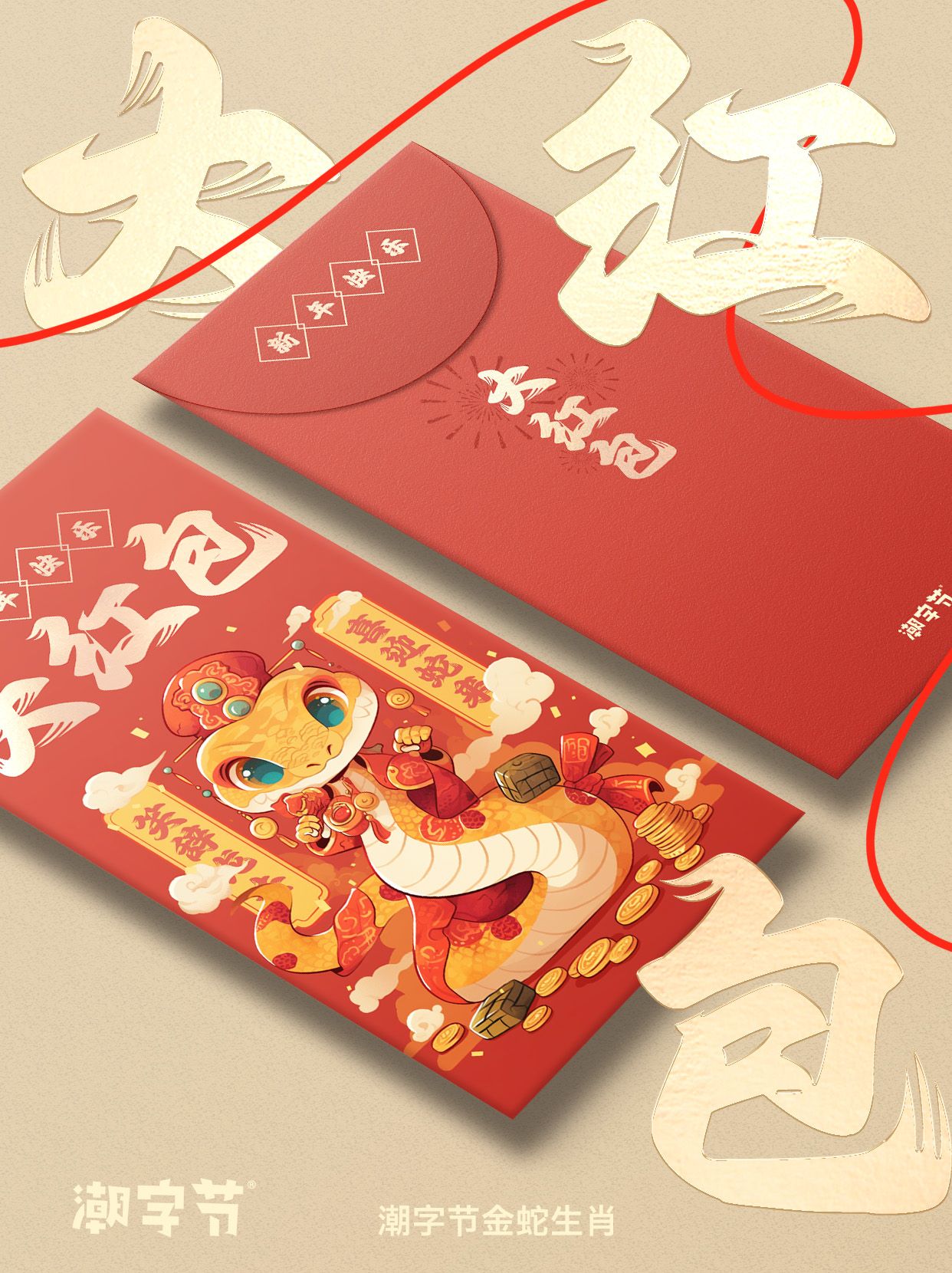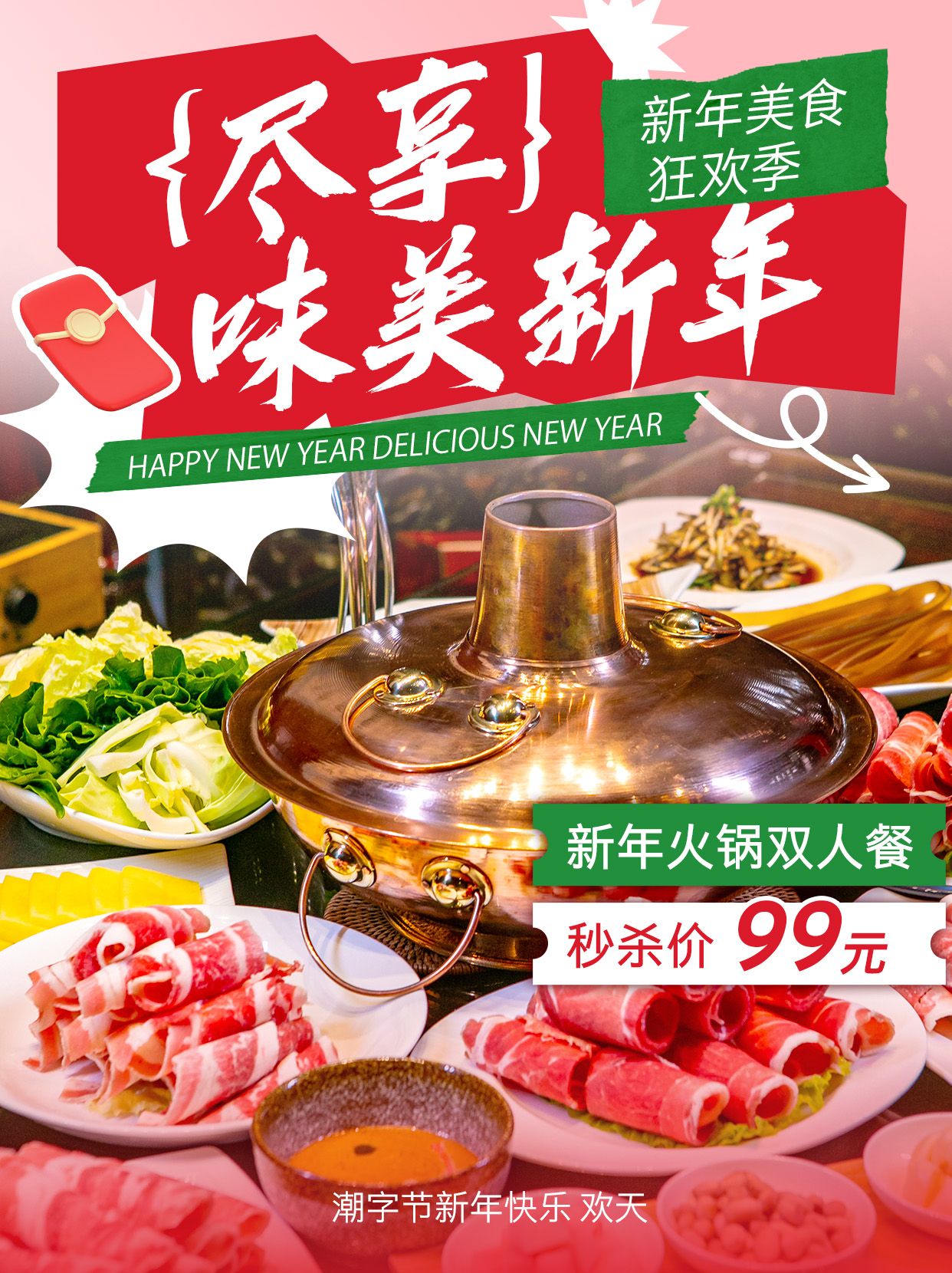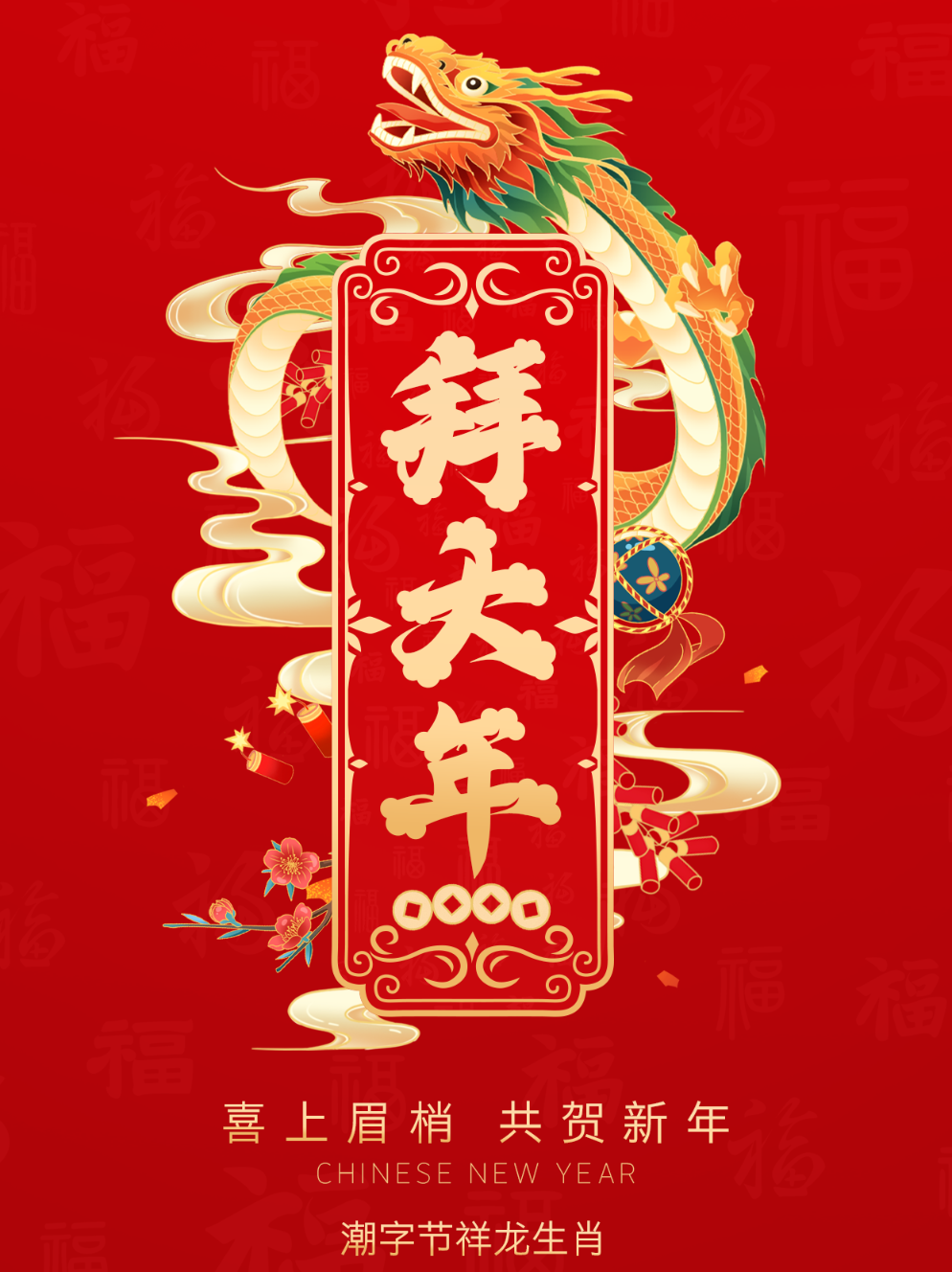
🎉揭秘三款国潮包装里常见的字体🎨潮字节字体大赏🐉
亲们,是不是每次看到那些充满国潮元素的包装设计,都忍不住想多看两眼?今天,就让我来揭秘三款让你包装瞬间提升格调的神级字体——“潮字节金蛇生肖”、“潮字节祥龙生肖”和“潮字节新年快乐”,保证让你的产品包装成为市场上的焦点!✨
1️⃣ 潮字节金蛇生肖 🐍
金蛇狂舞,寓意着财富与智慧。这款字体将传统生肖元素与现代设计完美融合,每一笔都透露着灵动与力量。无论是用于新年礼盒、还是限量版商品包装,金蛇生肖的华丽与神秘都能让你的产品脱颖而出,成为消费者心中的“C位”。
2️⃣ 潮字节祥龙生肖 🐉
龙,作为中华民族的象征,代表着尊贵与力量。潮字节祥龙生肖字体,将龙的威严与优雅展现得淋漓尽致。无论是高端白酒、还是精致茶具的包装,祥龙生肖的加入都能让产品瞬间提升档次,彰显出浓厚的文化底蕴与不凡品味。
3️⃣ 潮字节新年快乐 🎊
春节将至,怎能少了节日氛围?潮字节新年快乐字体,以其喜庆而不失格调的设计,成为节日包装的首选。无论是年货礼盒、还是新年贺卡,这款字体都能让你的祝福更加生动有趣,让收到礼物的人感受到满满的节日喜悦。
三款字体,三款风情,每一款都蕴含着浓厚的国潮韵味与文化底蕴。用它们来装点你的产品包装,不仅能让消费者眼前一亮,更能传递出你对传统文化的尊重与热爱。🎁💖